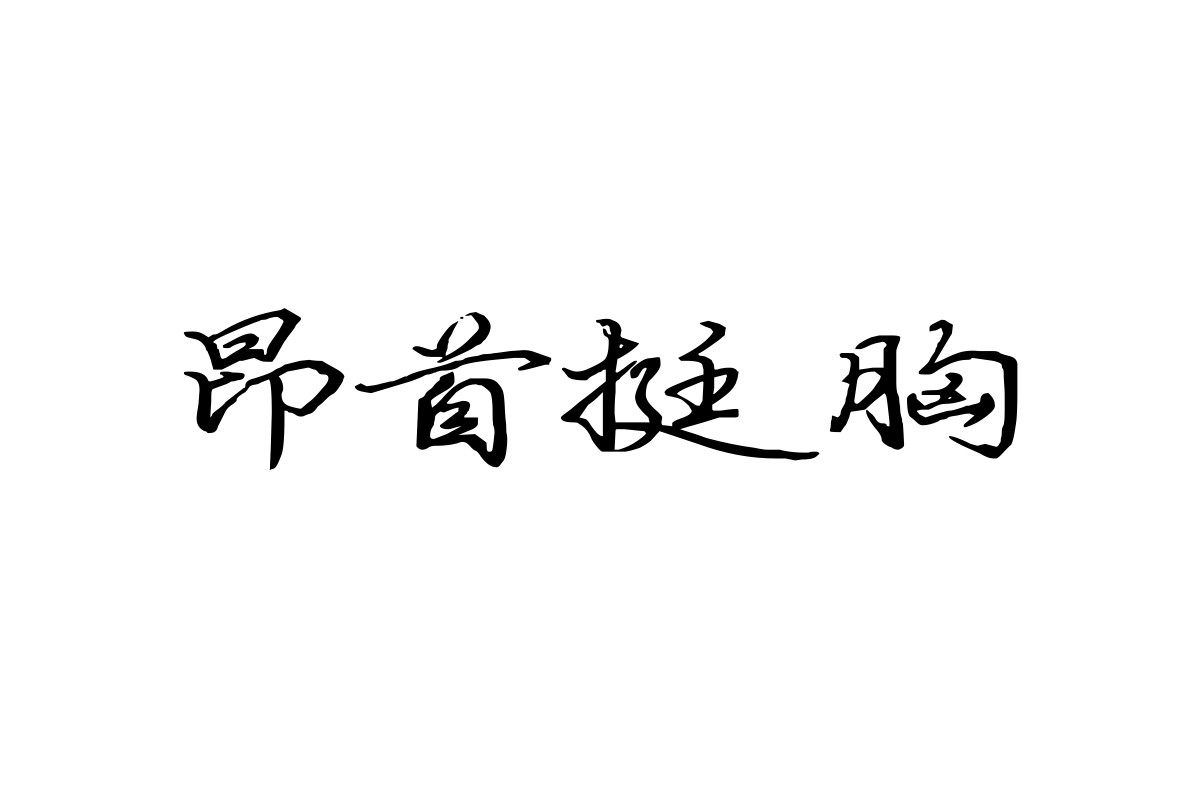
段宁硬笔朵云体是一套独特的汉字书写风格,由中国书法家段宁创作。这套字体以其独特的笔画结构和流畅的线条而闻名,给人以优雅、灵动的感觉。
段宁硬笔朵云体的笔画粗细不一,既有粗犷的线条,又有精细的小细节。这种笔画结构使得字体看起来既有力度又不失柔和,给人一种强烈的视觉冲击力。
此外,段宁硬笔朵云体的字形也具有很高的辨识度。每个字都呈现出独特的形态,既有传统的美感,又不失现代感。这使得这套字体在各种场合都能展现出其独特的魅力。
总的来说,段宁硬笔朵云体是一种非常独特且富有表现力的字体,它不仅适合用于书法作品的创作,也非常适合用于各种设计领域的应用。